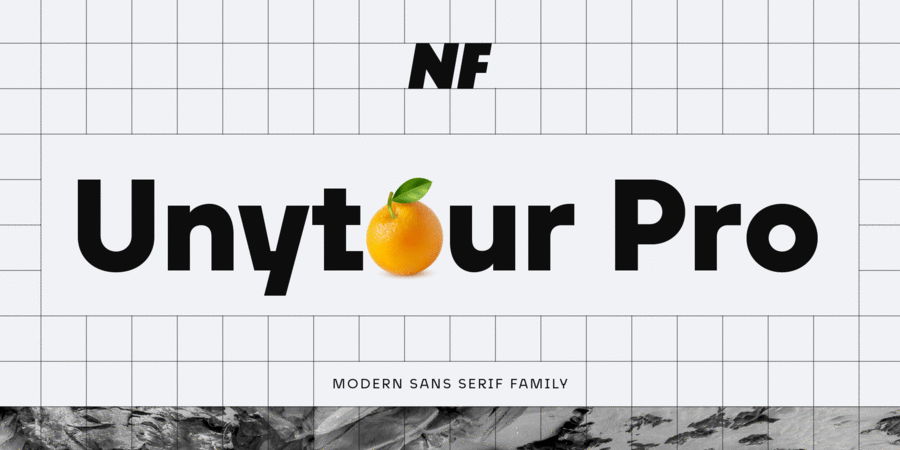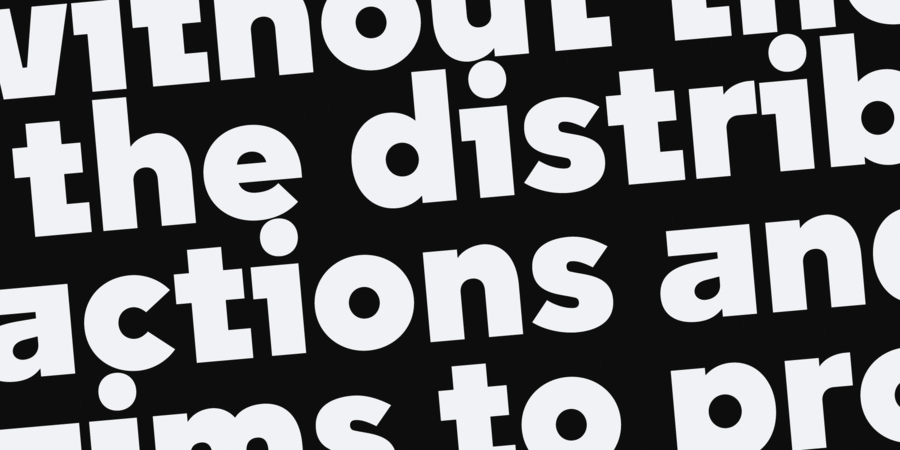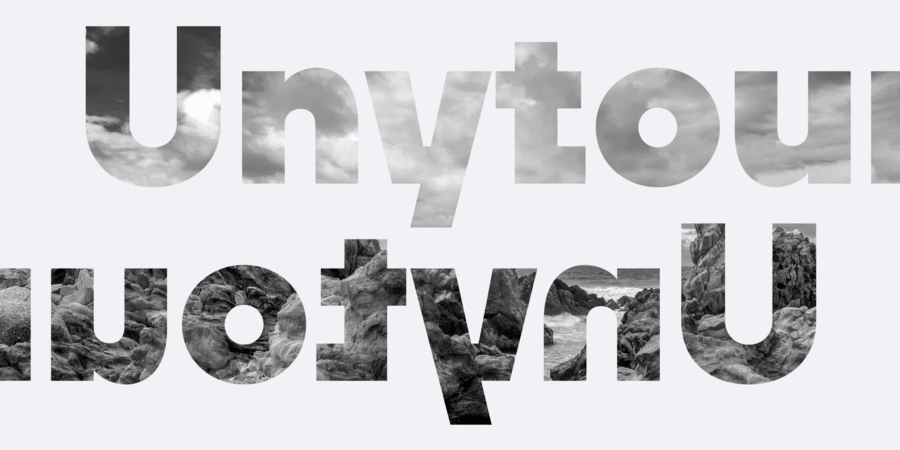
Опис гарнітури Unytour Pro — це сучасне сімейство шрифтів без зарубок, що містить 60 шрифтів. Воно включає 10 товщин, від Thin до Heavy, з відповідними курсивами. Кожна товщина пропонує 1,000 гліфів, альтернативні символи (A, G, I, R, a, l, t, y, Л, б, и, м, ф, у) та функції OpenType. Unytour Pro відзначається високою читабельністю та ідеально підходить для логотипів, реклами, пакування, обкладинок книг, журналів, заголовків, корпоративних стилів та іншого. Шрифт розробив Микола Савчук у 2024 році.